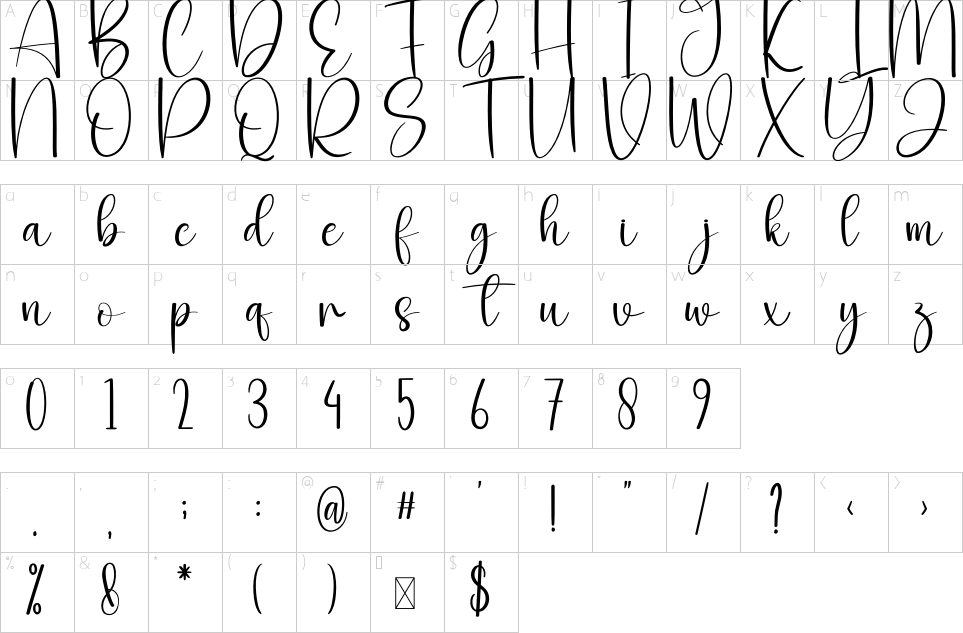
Descubra a elegância da Samantha Font, uma fonte grátis perfeita para seus projetos digitais. Desenhada pelo talentoso scratchones, Samantha oferece um visual moderno e sofisticado que se adapta perfeitamente a texturas variadas, desde layouts de newsletters até design gráfico. Se você está buscando uma fonte de qualidade para trabalhos online e impressos, a Samantha Font é uma escolha segura. Esta fonte foi baixada 236 vezes, o que sugere seu valor e relevância no mercado. Instale-a em sua próxima criação e experimente a sofisticação da Samantha.